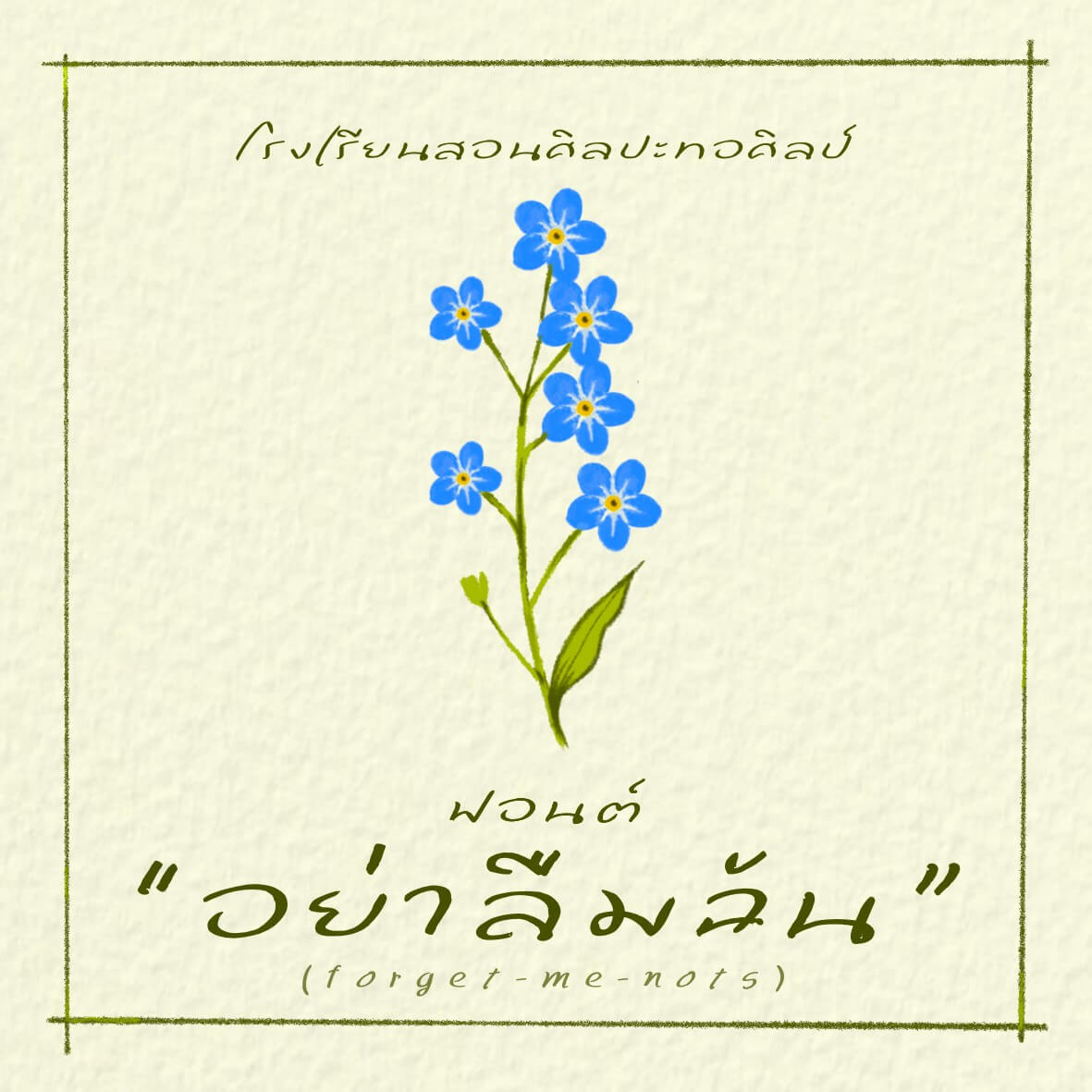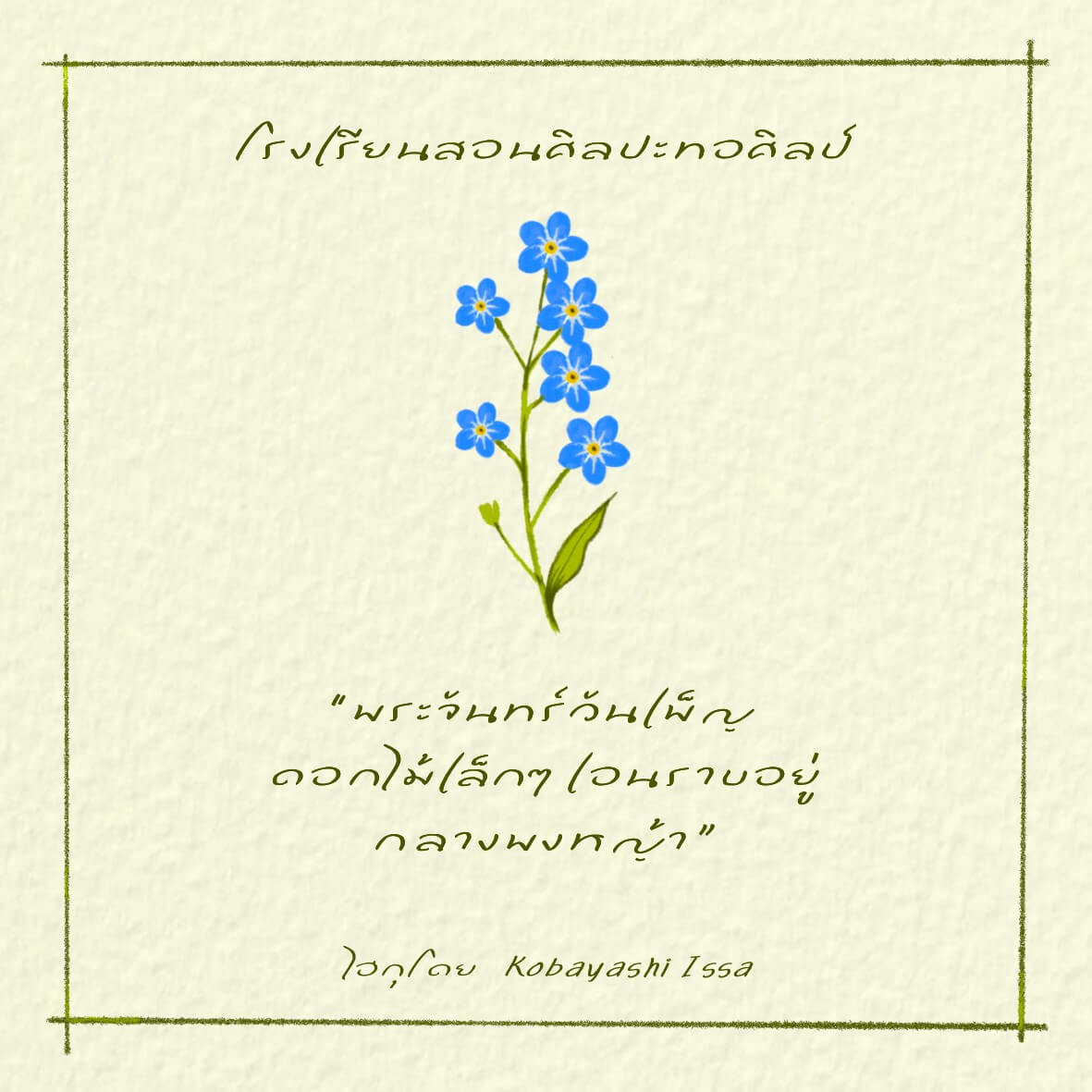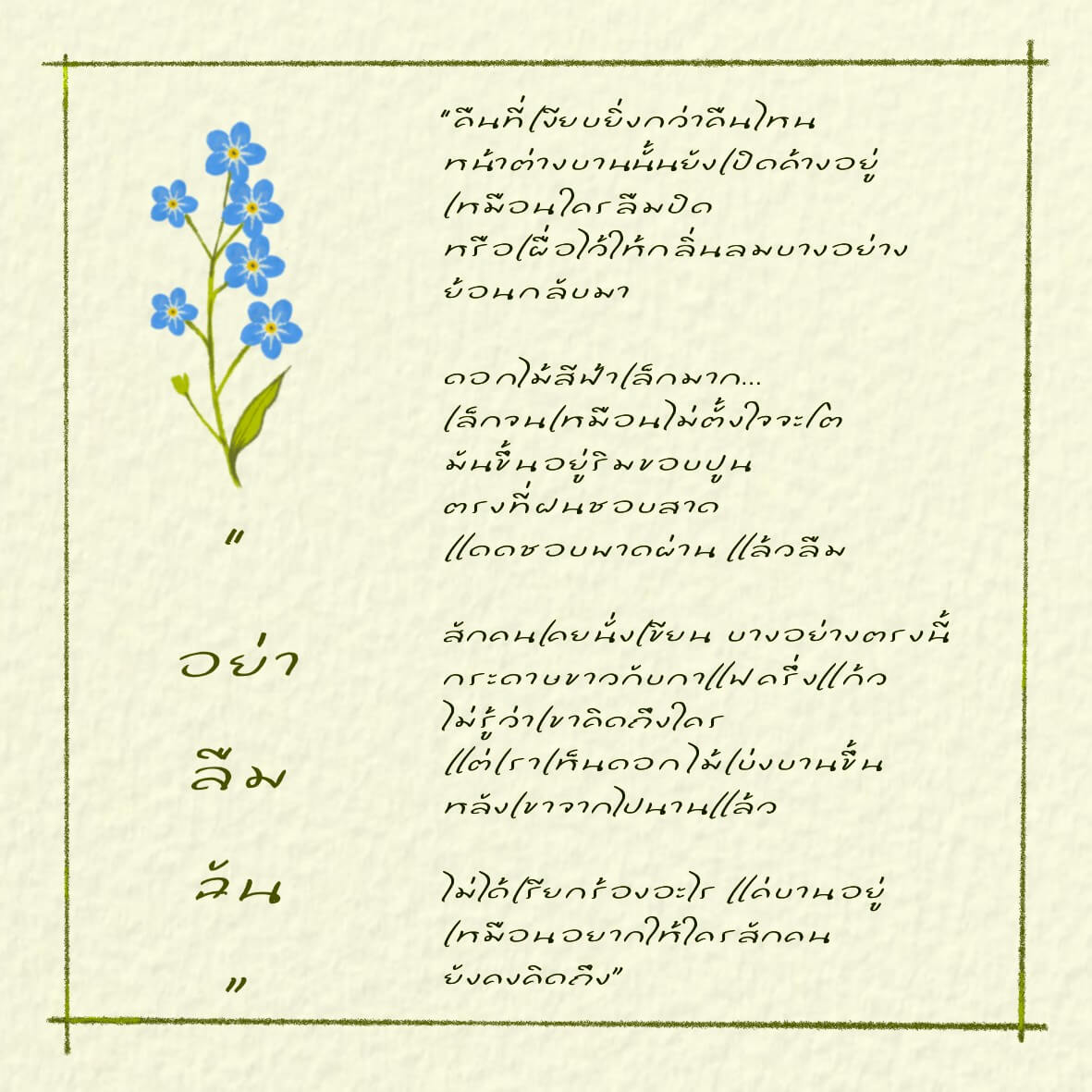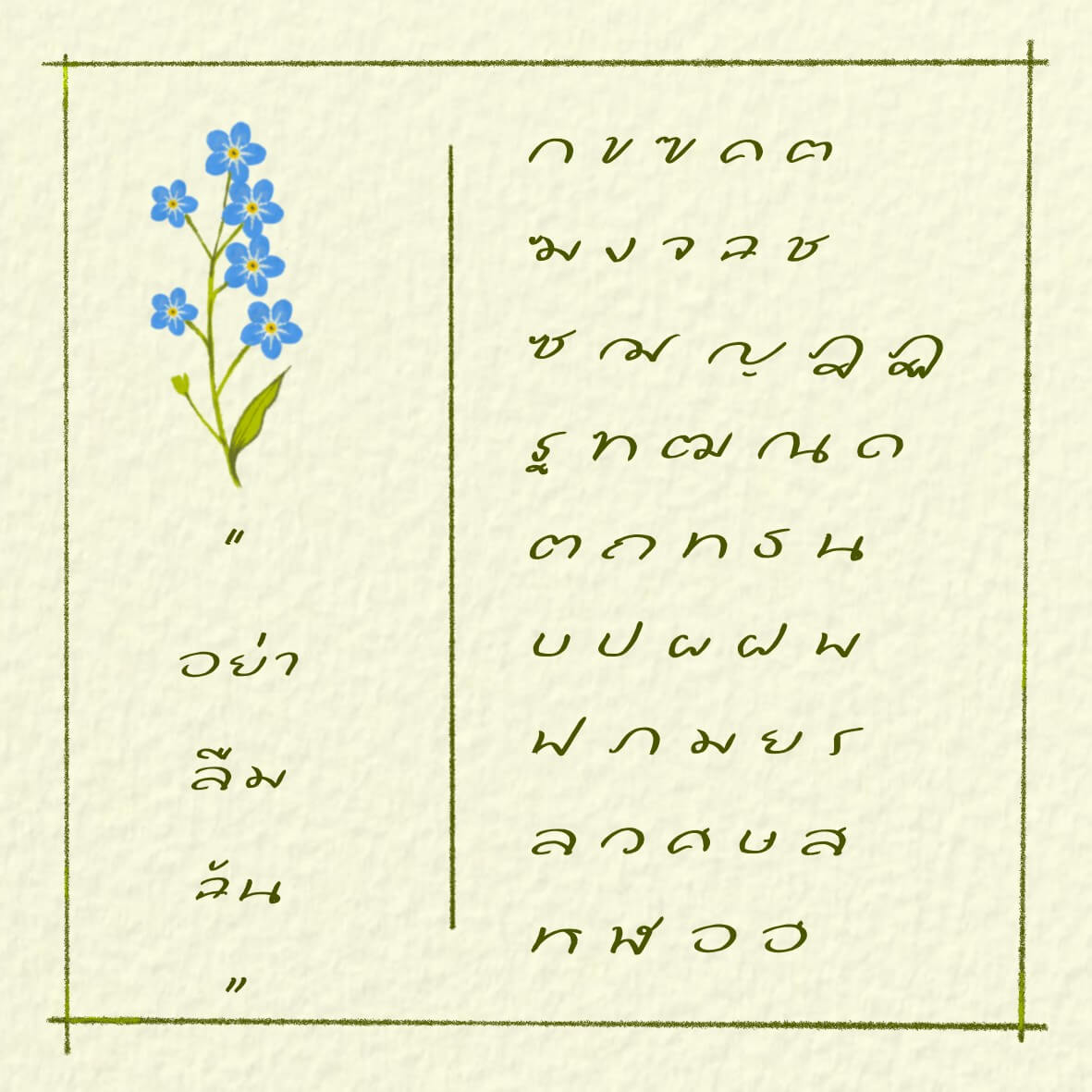
ฟอนต์ “ทอศิลป์ อย่าลืมฉัน” โดย โรงเรียนสอนศิลปะทอศิลป์ ตอนแรกจะตั้งชื่อว่า “เล็กน้อยมหาศาล” แต่คิดไปคิดมาเอาเป็น “อย่าลืมฉัน” เพราะกว่า
พัฒนามาจากฟอนต์ ทอศิลป์ คงยังคิดถึง
มีสองน้ำหนักคือ ตัวปกติ และตัวลายบรัช
ทอศิลป์ อย่าลืมฉัน (Torsilp YaLuemChan)